Les bests of de la fonderie The Northern Block.
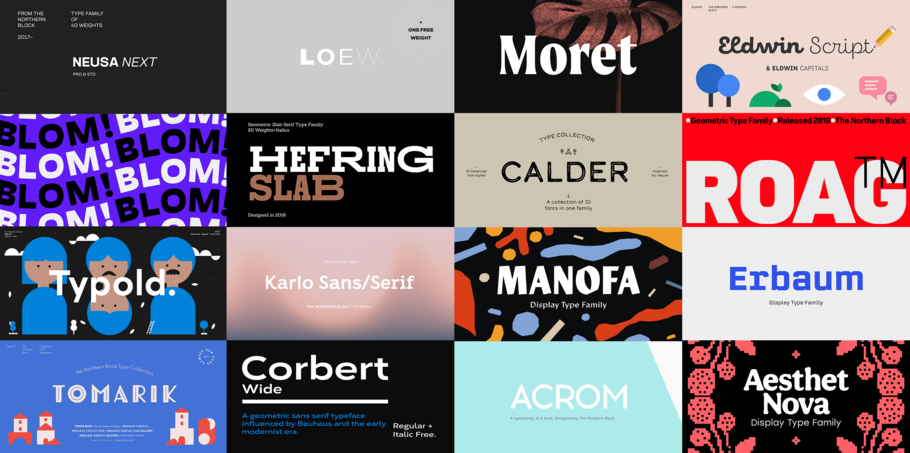
The Northern Block.
Fondée en 2006 par Jonathan Hill, The Northern Block est une fonderie collaborative reconnue internationalement pour la production de polices modernistes pour les marques, les créatifs et les fabricants. L'équipe internationale hautement qualifiée et enthousiaste de The Northern Block conçoit et développe des polices de caractères primées pour le commerce de détail et personnalisées et fait avancer la conception d'écritures non latines, notamment l'arabe, le cyrillique, le grec et l'hébreu.
Neusa Next
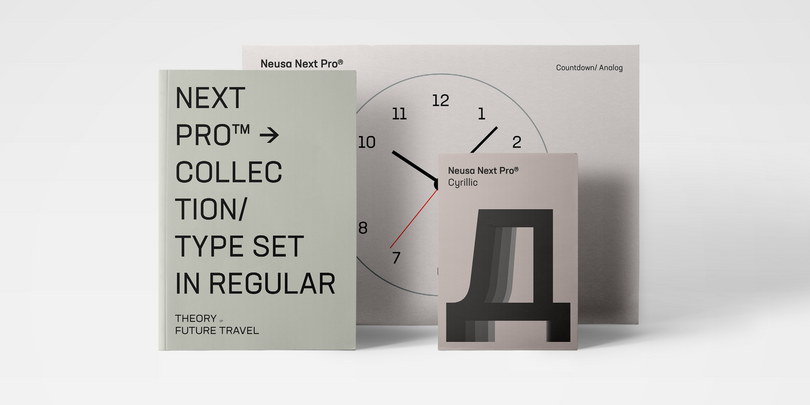
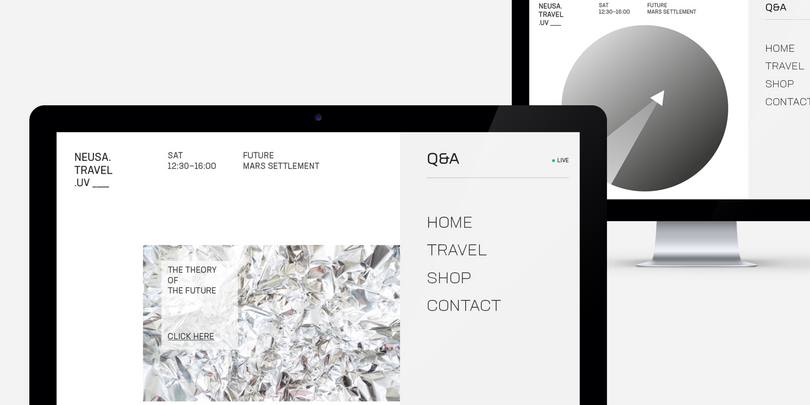
Neusa Next est une famille géométrique sans empattement conçue par Maria V. Pigoulevskaya. Le design s’inspire des travaux du design suisse et des premières explorations spatiales, notamment de la couverture du programme Apollo de 1969 par le magazine “Life”. Sa large gamme de graisses, de largeurs et d’italiques assortis fournit au concepteur une palette typographique complexe et riche. Conçue et publié sous le nom de Neusa en 2012, elle a été initialement conçue comme une famille de caractères aux proportions condensées. Adaptée au texte, elle était dotée de caractéristiques distinctives qui se distinguaient spécialement dans les grands affichages.
Aujourd’hui, Neusa Next reprend l’idée originale, en élargissant son jeu de caractères au cyrillique et en introduisant trois autres largeurs : Compact, Regular et Wide, chacun ayant sa propre personnalité. Neusa Next Std prend en charge les langues basées sur le latin, tandis que Neusa Next Pro couvre également le cyrillique.
Moret
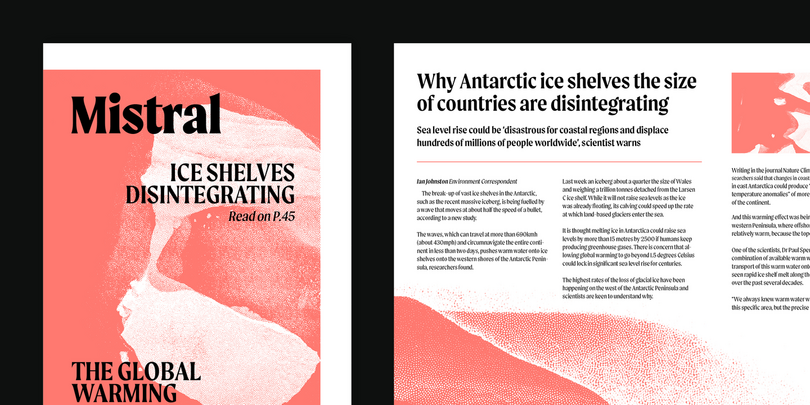
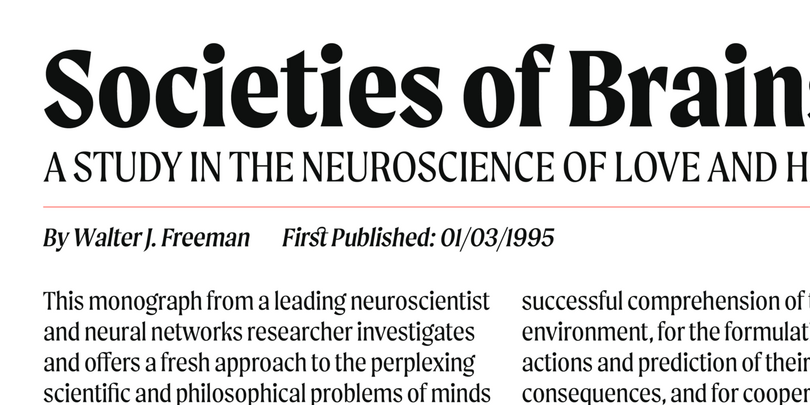
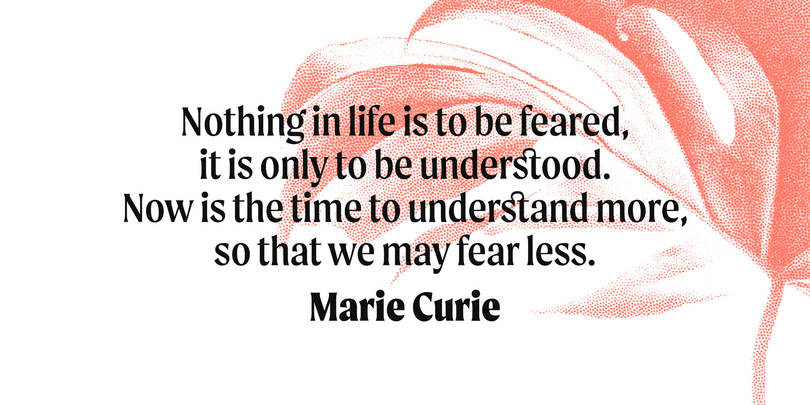
Moret est une famille de polices d’affichage à empattements inspirée par la peinture de signes européenne du XXe siècle. Elle combine plusieurs concepts calligraphiques pour créer une police de caractères unique, dynamique et emphatique. Disponible en 5 graisses et 2 styles (vertical et oblique), Moret est bien équipée pour apporter des solutions claires à une variété de situations et de contextes tels que les éditoriaux et les titres. Avec 466 glyphes par police, Moret prend en charge 94 langues différentes. Les caractéristiques OpenType inclus les caractères inférieurs, supérieurs, les fractions, les chiffres tabulaires et les ligatures.
Blom
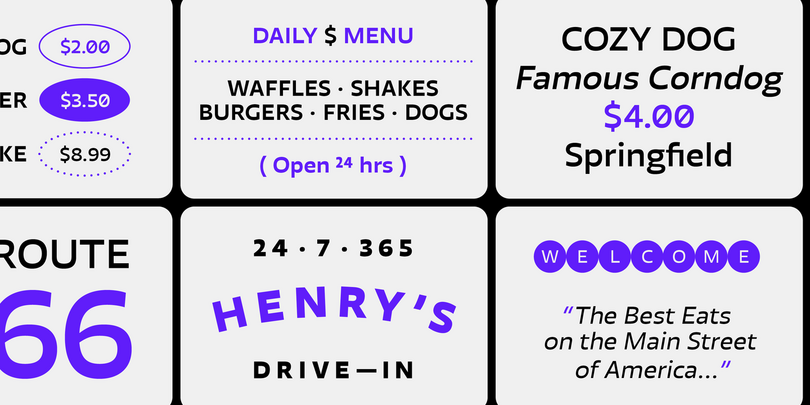
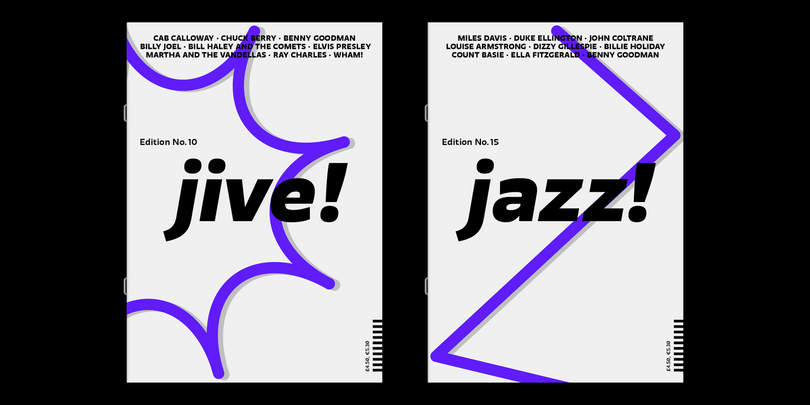
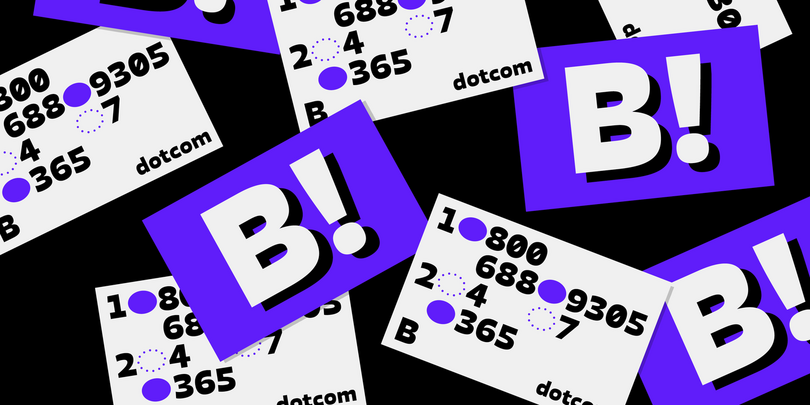
Blom est une police sans empattement humaniste au caractère subtilement carré, en contraste inverse. La combinaison d’horizontales lourdes et de géométrie moderne donne à la police une esthétique visuelle unique tout en rendant les petits textes parfaitement lisibles. Blom renverse la tendance des formes de lettres conventionnelles en faveur d’une police de caractères polyvalente et originale, qui est à la fois inventive dans son style et complètement fonctionnelle dans un large éventail d’utilisations.
Elle contient 463 caractères, six graisses avec italiques assorties et cinq variantes de chiffres. Les caractéristiques OpenType comprennent les inférieurs, les supérieurs, les fractions, les zéros barrés, les formes sensibles à la casse, les ligatures et le support linguistique couvrant l’Europe occidentale, du Sud et centrale.
Tomarik
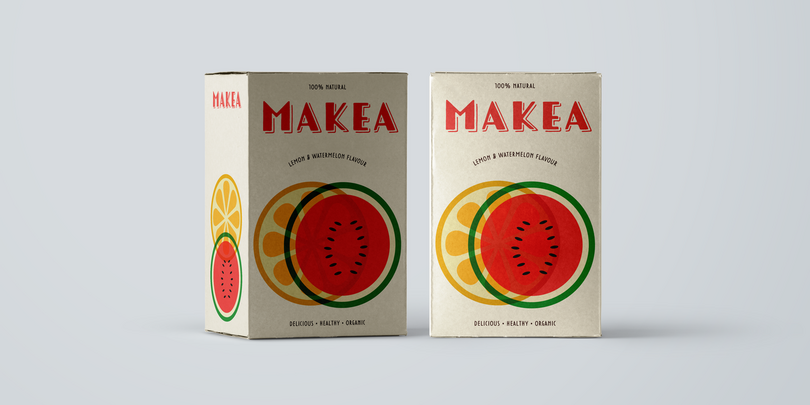
Tomarik est une collection dynamique de caractères dessinés à la main et un ajout ludique à tout dépôt créatif. Assemblée avec l’idée de “pick-and-mix” en tête, elle offre une grande variété de saveurs et de zestes. Tomarik se caractérise par neuf graisses distinctives et comprend des caractéristiques OpenType telles que les fractions, les inférieurs et les supérieurs.
Calder
Inspirée par la recherche du plein air, Calder a commencé comme une expérience personnelle et un effort pour exprimer et partager l’esprit d’aventure lié à ce mouvement renouvelé et croissant. Elle comprend 10 styles et offre deux voix distinctes : un script ludique semi-connecté et une sélection de sans serifs subtils mais authentiques. Conçue comme une boîte à outils de styles qui se complètent, la famille est un outil visuel unique et engageant.
Typold
Typold est née du désir d’améliorer les formes géométriques et de dépasser les réalisations antérieures grâce à des méthodes de travail collaboratives et au partage des connaissances. Le résultat est un sans empattement moderne finement équilibré, construit à partir d’apports mathématiques, des besoins des typographes et de la main et œil naturels d’un artisan.
Elle contient huit graisses et les italiques correspondantes, trois largeurs distinctes, 1000 caractères avec un “a” et un “y” minuscules, des petites capitales, 12 variantes de chiffres et des caractéristiques OpenType telles que les caractères inférieurs, supérieurs, les fractions, la ponctuation sensible à la casse, les symboles étendus, y compris les émojis, et un support linguistique couvrant l’Europe occidentale, du Sud et centrale.
Karlo
Inspirée par les écrits du calligraphe Edward Johnston, la famille avance dans deux directions vers les graisses les plus lourdes. Johnston a démontré que le stylo à plume large peut produire différents styles d’écriture. Ainsi, une graisse lourde présente un faible contraste de trait humaniste (KarloSerifBold et KarloSansBold), tandis qu’une autre présente un fort contraste de trait d’axe vertical avec des références aux polices de caractères de travail du XIXe siècle (KarloOpen). Ce dernier s’inspire de la démonstration du stylo à plume large faite par Johnston, où il suggérait de fixer deux crayons ensemble. Chaque crayon représentant un bord du stylo, il devient plus évident de voir comment le stylo fonctionne en écriture.
Manofa
Manofa est une police de caractères calligraphique sans empattement. Elle est inspirée du Lydian de Warren Chappell et est issue d’expériences sur la form de la lettre “O”. Le résultat est un affichage contemporain, net et sculptural. Elle contient quatre graisses, les italiques correspondantes, deux largeurs, des caractères alternatifs ainsi que les caractéristiques OpenType.